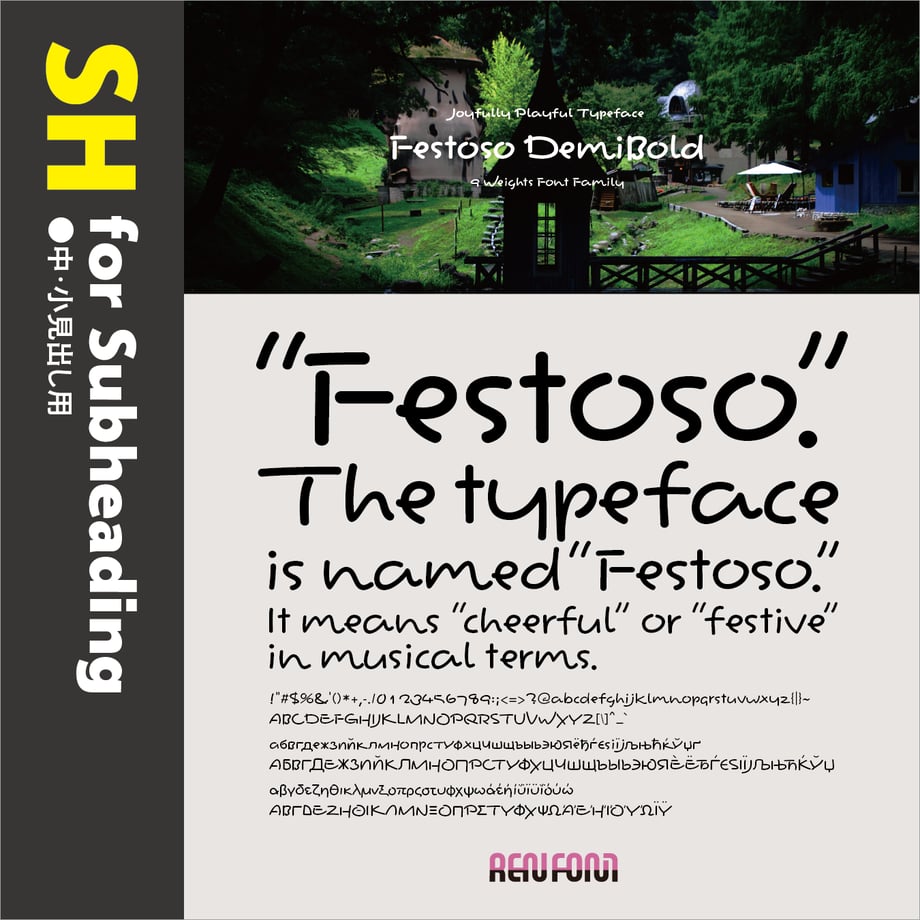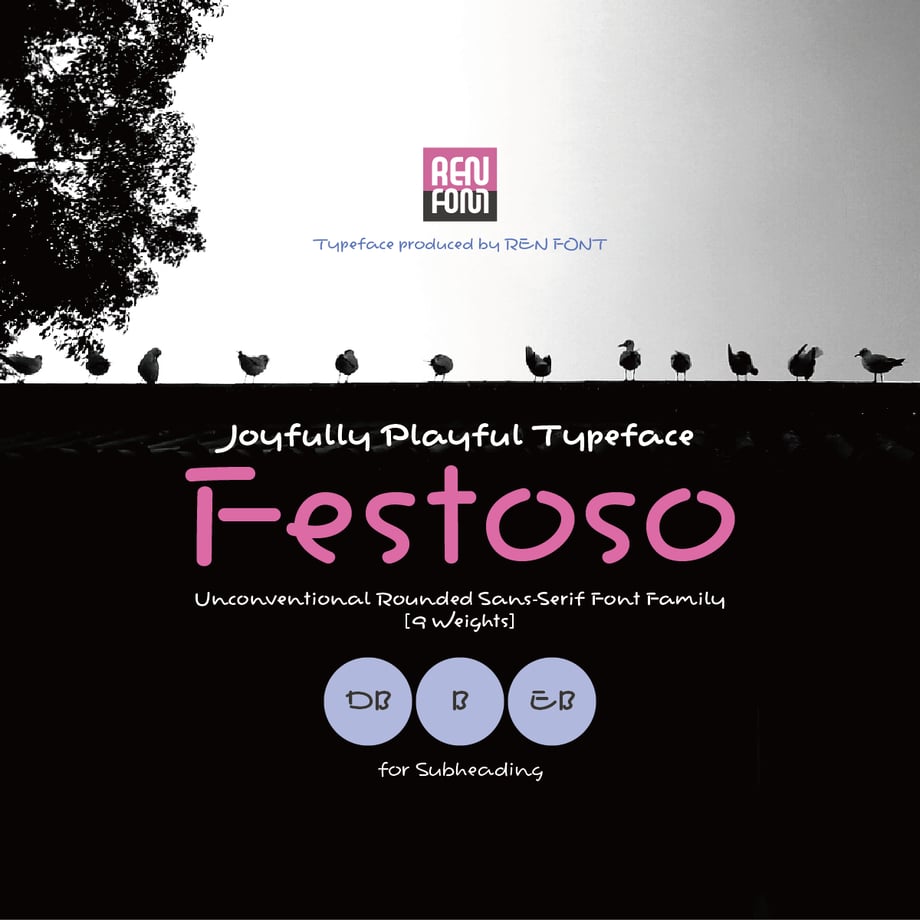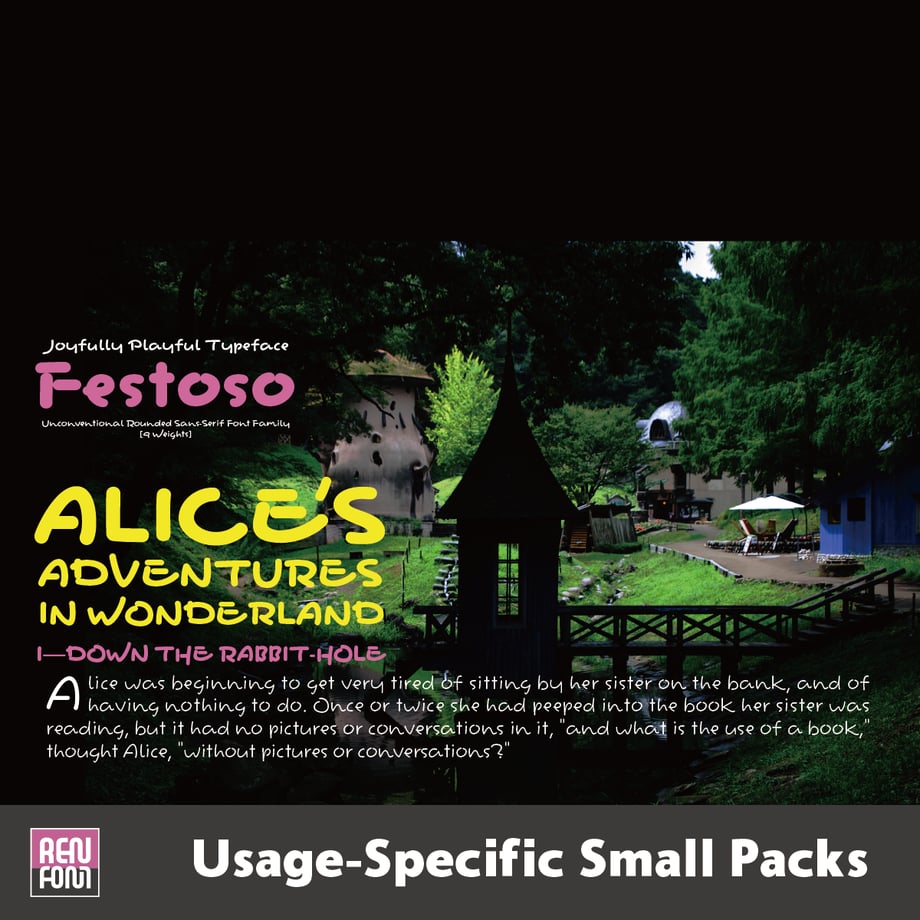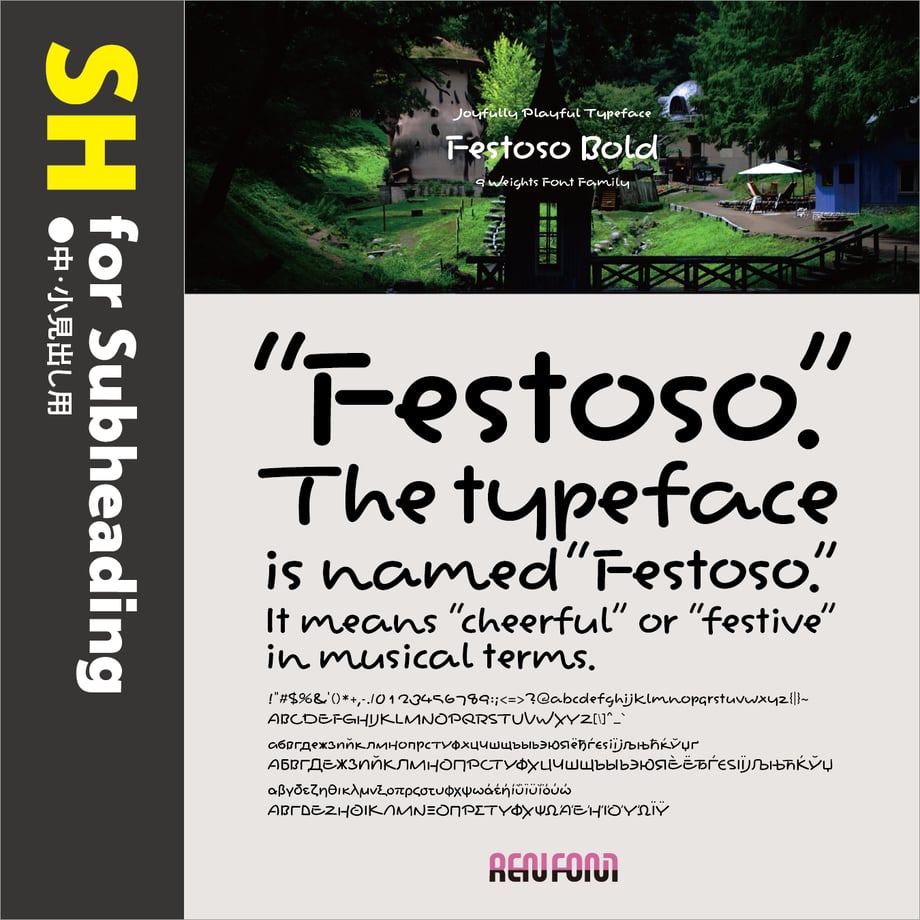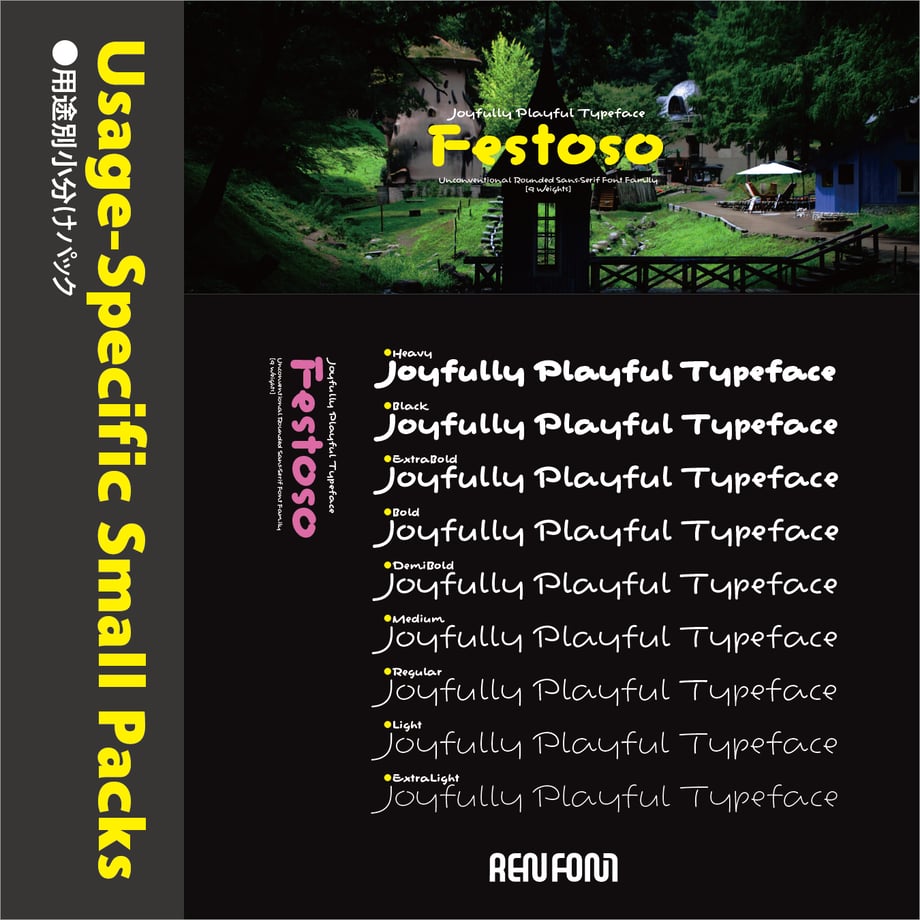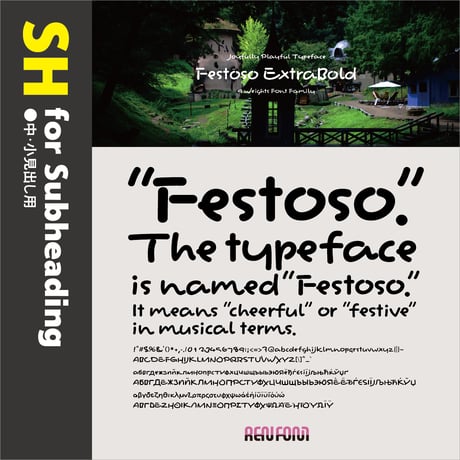
Festoso-SH(中・小見出し用)DB/B/EB
■About Festoso
Designed as a Companion to “Hommaru-Kana”
As Festoso was created as the Latin companion to Hommaru-Kana, it naturally reflects the distinctive characteristics of Honmaru-Kana in its design.
While our general policy is to design companion Latin scripts in a relatively orthodox style, Festoso was developed as a script typeface to maintain consistency with the playful and expressive nature of Hommaru-Kana.
This typeface is based on the everyday handwriting of our type designer, Kazuo Kanai.
It features a uniquely rounded form with subtle traces of brush lettering.
The family consists of nine weights, ranging from Extra Light (EL) to Heavy (H).
■Festoso について
「ほんまるかな」の従属書体として設計
“Festoso” は「ほんまるかな」の従属欧文として制作されたため、そのデザインには当然ながら「ほんまるかな」の持つ特徴が反映されています。
当社では、従属欧文は比較的オーソドックスな書体で設計する方針を基本としていますが、“Festoso” に関しては、「ほんまるかな」の持つ遊び心や表情豊かさとの整合性を保つために、あえてスクリプト体(手書き風書体)でデザインしました。
この書体は、当社タイプデザイナー金井和夫の普段使いの文字をベースとしてデザインされたものです。わずかに筆文字の痕跡を残した、一風変わった丸文字的フォルムイメージを持っています。「EL(エクストラライト)」から「H(ヘビー)」までの、9ウェイトで構成されています。
■Characteristics of Festoso
The typeface is named “Festoso.”
Festoso is an Italian musical term that means “cheerful” or “festive.” In musical contexts, it instructs the performer to play in a lively, joyful, almost celebratory manner.
This typeface, Festoso, captures that same festive spirit. Some characters bounce energetically, while others come to a sharp, sudden stop. Unpredictable and full of variety, it’s a rhythmically expressive and boldly unconventional design. Just using it lifts your spirits—it’s a font that brings joy, unconditionally.
The Five Guideline Lines Are Largely Ignored
In Western typography, beauty is typically achieved through adherence to five standard guideline lines: ascender, cap height, mean (x-height), baseline, and descender. These provide a natural sense of order and harmony.
However, Festoso treats these baseline structures as mere guidelines. By intentionally breaking away from them, it creates an irregular rhythm that adds playfulness and cheerfulness to the entire typeface. As its name suggests, it has a joyful and lively character.
Extremely Wide Set Width
As a result of its script-style design, some characters have an exceptionally wide set width. While this makes the typeface less suitable for long-form text, it produces a distinctive visual effect in shorter phrases and headlines.
Incorporating the charm of 'hané' (brushstroke flicks)
The finishing strokes of [a], [h], [j], [k], [l], [m], and [n] are deliberately designed to incorporate the characteristic "hané" (upward flick). These are relatively frequently used letters, and they naturally add a lively rhythm to the text. Meanwhile, the Cyrillic and Greek characters have been designed more modestly to maintain legibility.
Deliberately Breaking the Rules with Capital Letters
The capital letters are intentionally designed with disrupted balance. For example, take the letter [A]—its apex (the pointed top) has been dramatically shifted to the right. At first glance, one might mistake it for italic. We took the boldest leap right at the beginning of the alphabet.
In addition, we altered the balance of other letters with a two-tiered vertical structure. For letters like [H], [K], [P], [R], [S], [X], and [Y], the visual center of gravity is intentionally placed on the opposite side from what’s typical. Meanwhile, letters like [B], [E], [F], and [G] feature exaggerated contrasts between their upper and lower halves, enhancing the rhythmic flow of the text.
Pair Kerning for Latin, Cyrillic, and Greek Scripts
In the Latin, Cyrillic, and Greek character sets, pair kerning has been applied to side bearings where proportional metrics alone could not adequately address awkward or unnatural spacing.
■Festoso の特長
この書体の名前は「Festoso(フェストーソ)」です。
Festoso はイタリア語の音楽用語で、「陽気な」「楽しい」といった意味があります。音楽においては、演奏を陽気に、お祭りのように明るく行うよう指示する際に使われる表現です。
この書体 Festoso も、まさにそのお祭りのような陽気さを表現しています。跳ねる文字もあれば、ピタッと止まる文字もあり、予測不可能でバラエティに富んだ、リズム感あふれる破天荒なデザインです。使っているだけで気分が高まり、無条件に楽しくなってくるフォントです。
5本の基準ラインは基本的に無視
欧文タイポグラフィでは、アセンダー、キャップハイト、ミーンライン(xハイト)、ベースライン、ディセンダーという5本の基準ラインに従うことで、自然な秩序と調和が生まれ、美しさが備わるのが一般的です。
しかし “Festoso” は、これらの基準ラインをあくまで「参考程度」として扱っています。意図的にこの構造を崩すことで、不規則なリズムが生まれ、書体全体に遊び心や陽気さが加わります。その名が示す通り、楽しく軽快な印象の書体となっています。
極端に広いセット幅
スクリプト風のデザインにした結果、いくつかの文字は非常に広いセット幅を持つようになりました。これにより長文にはあまり適しませんが、短めの文章や見出しでは独特の視覚効果を発揮します。
“跳ね(筆の跳ね上げ)”の魅力を取り入れる
[a]、[h]、[j]、[k]、[l]、[m]、[n] の収筆には、意図的に「跳ね」の特徴を取り入れています。これらは比較的使用頻度の高い文字であり、文章に自然と軽快なリズムをもたらします。一方で、キリル文字やギリシャ文字については、可読性を考慮して控えめなデザインにしてあります。
あえてセオリーを崩した大文字
大文字は、意図的に重心のバランスを崩したデザインになっています。たとえば [A]。アペックス(上部の尖った部分)を大きく右にずらしています。一見すると「イタリック体かな?」と錯覚するほどです。アルファベットの最初の文字で、最も大胆な試みに挑みました。
また、上下2段構造を持つ他の文字についても、[H]、[K]、[P]、[R]、[S]、[X]、[Y] などは、本来とは逆の位置に重心を置いています。[B]、[E]、[F]、[G] では、上下のコントラストを極端にすることで、文字全体により大きなリズムを生み出せるようにしています。